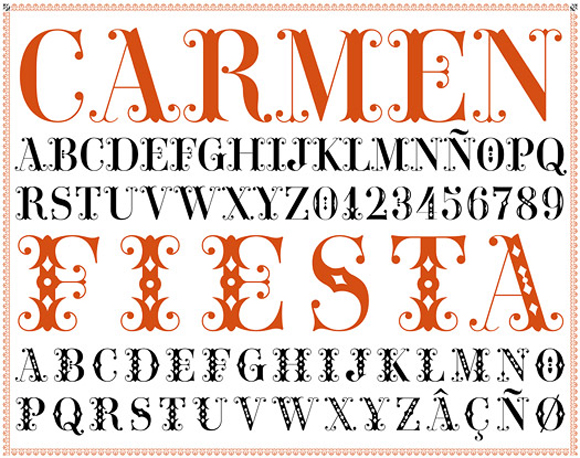
El diseñador tipográfico Andreu Balius nos presenta su última creación Carmen FIESTA. Se trata de una tipografía con un fuerte impacto visual que basa sus formas en las tipografías ornamentadas que aparecieron durante el siglo XIX y en concreto la podemos encuadrar perfectamente en la categoría de las «toscanas» . Sus remates extendidos y bilaterales acabados en un rasgo decorativo en forma circular, la decoración interior en sus astas y el fuerte contraste en los trazos auguran una utilidad eminentemente decorativa en todo tipo de usos en los que la tipografía sea el principal foco de atención.